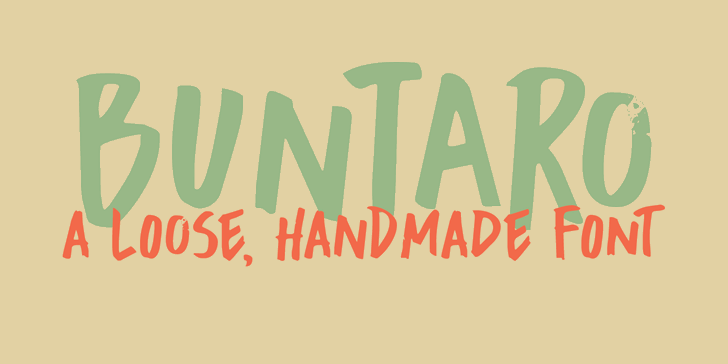
A DK Buntaro Font é uma elegante tipografia inspirada nos antigos modelos typewriters, oferecendo um charme retro que se adapta perfeitamente para ambientes digitais vintage. Se você está procurando por uma fonte com personalidade única e moderna, esta pode ser a escolha ideal. Feita pelo designer Hamilton, ela possui uma abrangência completa, incluindo todo o conjunto de caracteres e extras disponíveis em seu site oficial (www.hanodedfonts.com). Para uso pessoal é totalmente gratuita, mas se você planeja usar essa fonte comercialmente ou em jogos, apps ou software, deve comprar a versão full que traz recursos adicionais como as ferramentas de correção de espaçamento entre caracteres e os direitos de embedder. Não use a Buntaro em jogos, aplicativos ou softwares sem autorização prévia. Visite seu site para obter uma licença adequada, ou leia o arquivo FAQ incluído no zip.